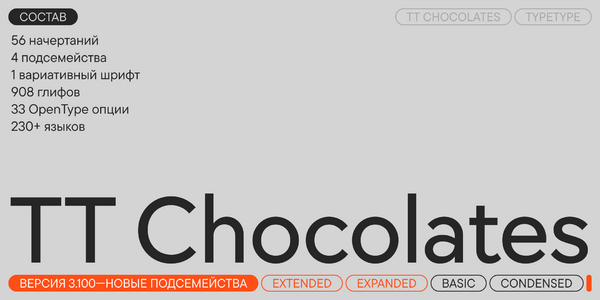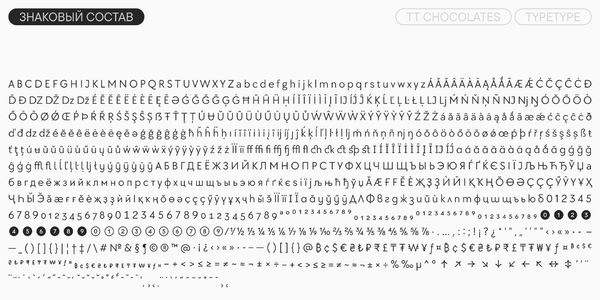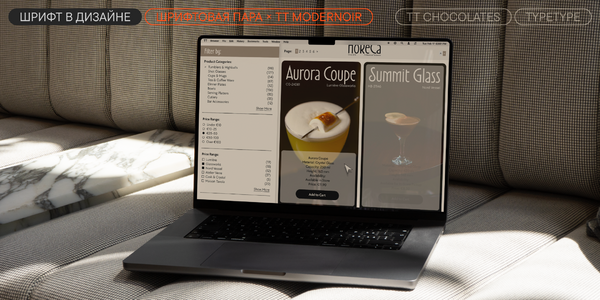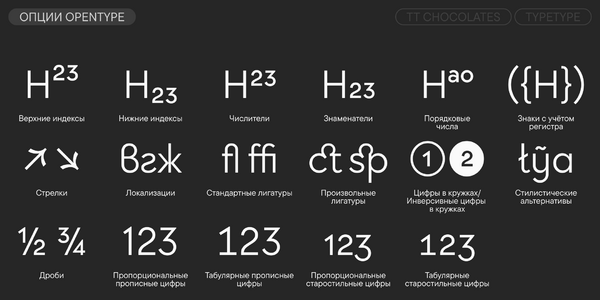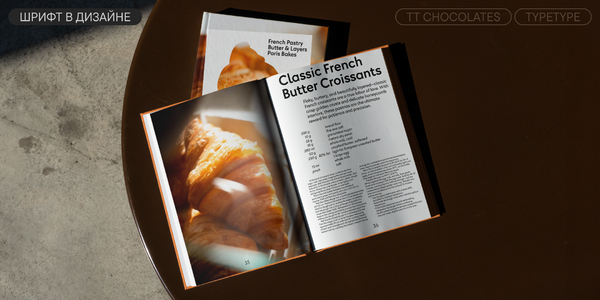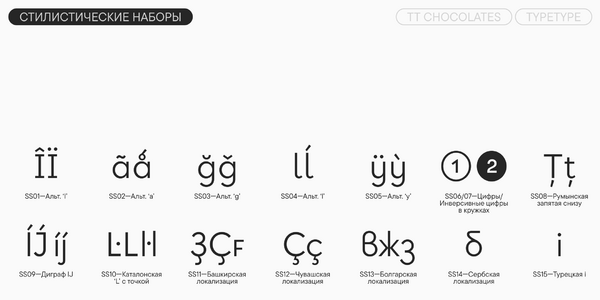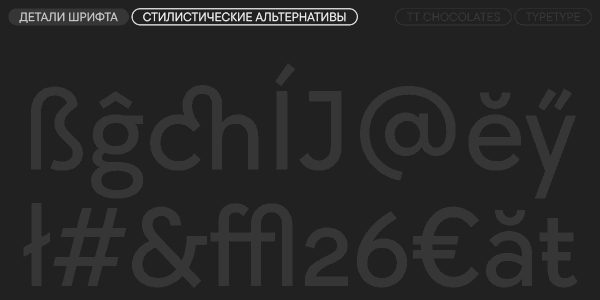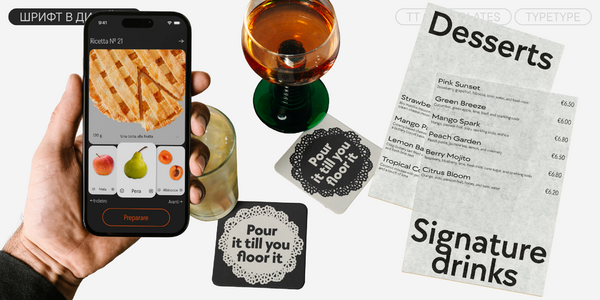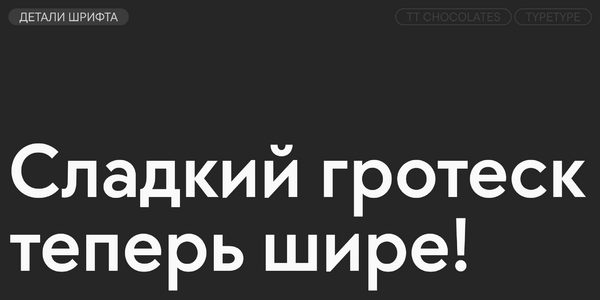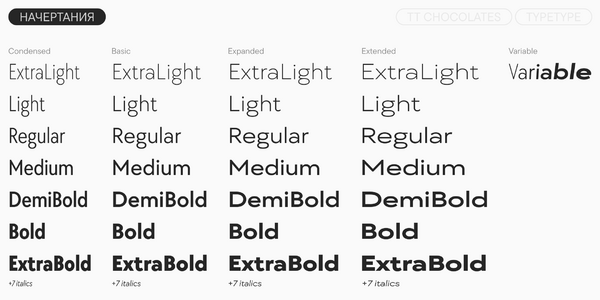
TT Chocolates
TT Chocolates — ТТ Чоколитс
Произносится «ТТ Чоколитс». «Chocolates» — производное слово от chocolate, в переводе с английского «шоколад». Буквы «TT» являются аббревиатурой названия компании.
TT Chocolates — изящный гуманистический гротеск с приятным дружелюбным характером. Зарекомендовал себя как шрифт для кондитерских, баров и ресторанов.
Третья реинкарнация легендарного шрифта TT Chocolates
Наше шрифтовое семейство TT Chocolates уже зарекомендовало себя среди пользователей как изящный гротеск для красивого дизайна. В 2023 году мы решили его полностью обновить, так как получили много сведений из исследования рынка гротесков, которое делали пару лет назад. Технически мы подправили огрехи в контурах и отрегулировали ритмику шрифта, а также добавили 35 кириллических и 16 латинских языков. В TT Chocolates 3.0 появилось 14 новых Condensed начертаний и новый вариативный шрифт, способный меняться по трем осям: ширине, толщине и наклону.
Третья версия шрифта снабжена большим количеством ОpenТype фич и стилистических сетов.
TT Chocolates — идеальный гротеск для кондитерской продукции.
TT Chocolates в дизайне
О гарнитуре TT Chocolates
Встречайте TT Chocolates версии 3.100!
Обновили самый сладкий шрифт TypeType: добавили новые подсемейства, знаки и функции.
TT Chocolates — изящный гуманистический гротеск с плотным набором и сбалансированными пропорциями, близкими к классическим. Это шрифт с приятным дружелюбным характером, который интуитивно воспринимается как что-то знакомое. Среди дизайнеров он зарекомендовал себя как идеальный шрифт для кондитерской продукции, но этим сфера применения гарнитуры вовсе не ограничивается.
В 2023 году мы решили полностью обновить шрифт, опираясь на масштабное исследование рынка гротесков. Мы узнали, куда двигаются тренды и чего хотят пользователи, и усовершенствовали TT Chocolates в соответствии с этой информацией. В частности, добавили узкое начертание (Condensed), в котором сохраняются аутентичные пропорции стандартного варианта. При этом TT Chocolates Condensed имеет более акцидентный характер, чем основное подсемейство, что позволяет решать ещё больше дизайнерских задач с помощью одной гарнитуры.